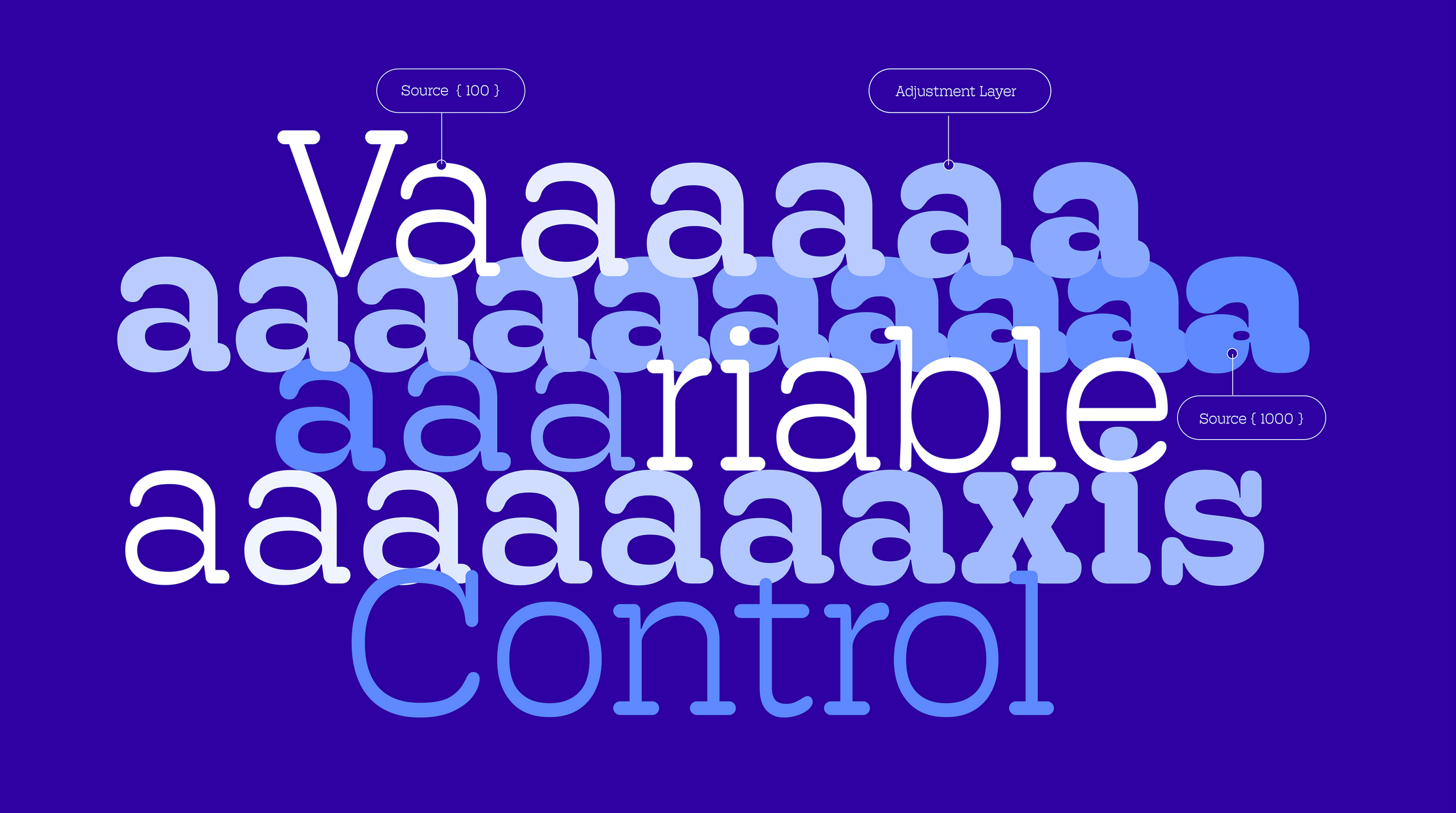
В последние годы мы наблюдаем настоящий бум в мире дизайна и типографики. Каждый день появляются новые шрифты, которые пытаются пробиться сквозь шум и привлечь внимание дизайнеров, но далеко не каждый из этих шрифтов истинный шедевр. Однако новый член семьи Hoss Round, шрифт Hoss Round Slab, кажется, способен не только захватить внимание, но и вдохновить дизайнерское сообщество. 🎨
Когда мы говорим о типографике, мы никогда не рассматриваем это просто как выбор шрифта. Это целая культура, живая и дышащая, постоянно меняющаяся и адаптирующаяся под современные запросы. В конце прошлого года Hoss Round Slab стал своеобразным приветом к корням, добавляя к своим безсерифным собратьям элементы традиционного блока серифов с легкой мягкостью. Это как добавить к восхитительному десерту неожиданный ингредиент и открыть для себя совершенно новые оттенки вкуса.
Подход с душой
Марк Канесо, создатель Hoss Round Slab, объясняет свой подход к обновлениям: "С несколькими годами разницы между этой новой версией и оригиналом, я сделал некоторые вдумчивые изменения с новым взглядом на набор символов." Кажется, что Хос тоже побывал на этой экспериментальной кухне, где каждое решение обдумано, словно это рецепт высокой кухни.
Когда Канесо сталкивался с задачей создания слеб-версии, он не просто добавил серифы к существующим формам. Он провел настоящую работу по пересмотру распределения массы, особенно в тяжелых стилях, что требовало полного перерисования каждой буквы. Чисто технически это очень сложный процесс, но результат говорит сам за себя.
Тонкая настройка шрифта
"Я добавил серифы в смесь, что подразумевало переосмысление распределения массы," — поясняет это Канесо. Изменения в заглавных буквах, таких как уменьшение перекладин в буквах A и H, наглядно демонстрируют, как даже малейшая деталь может оказать влияние на общую эстетическую гармонию шрифта.
Работа по адаптации шрифта к различным стилям – это не только техническое задание; это также искусство. Каждый символ требует своего подхода, и Канесо явно наслаждается этим процессом, что позволяет создать нечто действительно уникальное.
Свобода творчества
"Я всегда даю себе свободу отклоняться от своих оригинальных идей, если появляется такая возможность," — говорит Канесо и это, безусловно, подчеркивает одну из важнейших Truths в дизайне: творчество не должно быть ограниченным. Его подход показывает, что иногда нужно пойти на риск, чтобы достичь реального величия.
Несмотря на все технологии и сложности, Hoss Round Slab имеет огромный потенциал в использовании. Марк видит его в качестве идеального кандидата для брендинга музыкальных фестивалей, упаковки товаров и вообще везде, где требуется свежий, современной подход к идентичности бренда. Как отметил Канесо: "Лучшая часть выпуска шрифта в мир заключается в том, что я не могу контролировать, как его используют другие."
Идентичность и культура
Когда мы говорим о создании бренда, о айдентике и дизайне, мы должны помнить, что шрифт – это не просто текст. Он рассказывает историю. С его помощью можно выразить эмоции, привлечь внимание и создать целую атмосферу. Hoss Round Slab уже готов поддерживать более 200 латинских языков, от вьетнамского до французского, и становится универсальным шрифтом для глобального контекста.
Hoss Round Slab доступен в 14 стилях, включая семь весов и курсивов. Однако настоящая сила этого шрифта в том, что он не просто работает — он вдохновляет. Каждый раз, когда вы видите его в использовании, кажется, что он рассказывает свою собственную историю. 💬
Итог
Впереди у нас новое увлекательное путешествие в мир типографики. Hoss Round Slab не просто шрифт — это шаг в сторону новой эры визуального повествования, где каждое слово имеет свою уникальную идентичность. Таким образом, мы можем с уверенностью сказать, что Hoss Round Slab – это больше, чем просто простой шрифт.